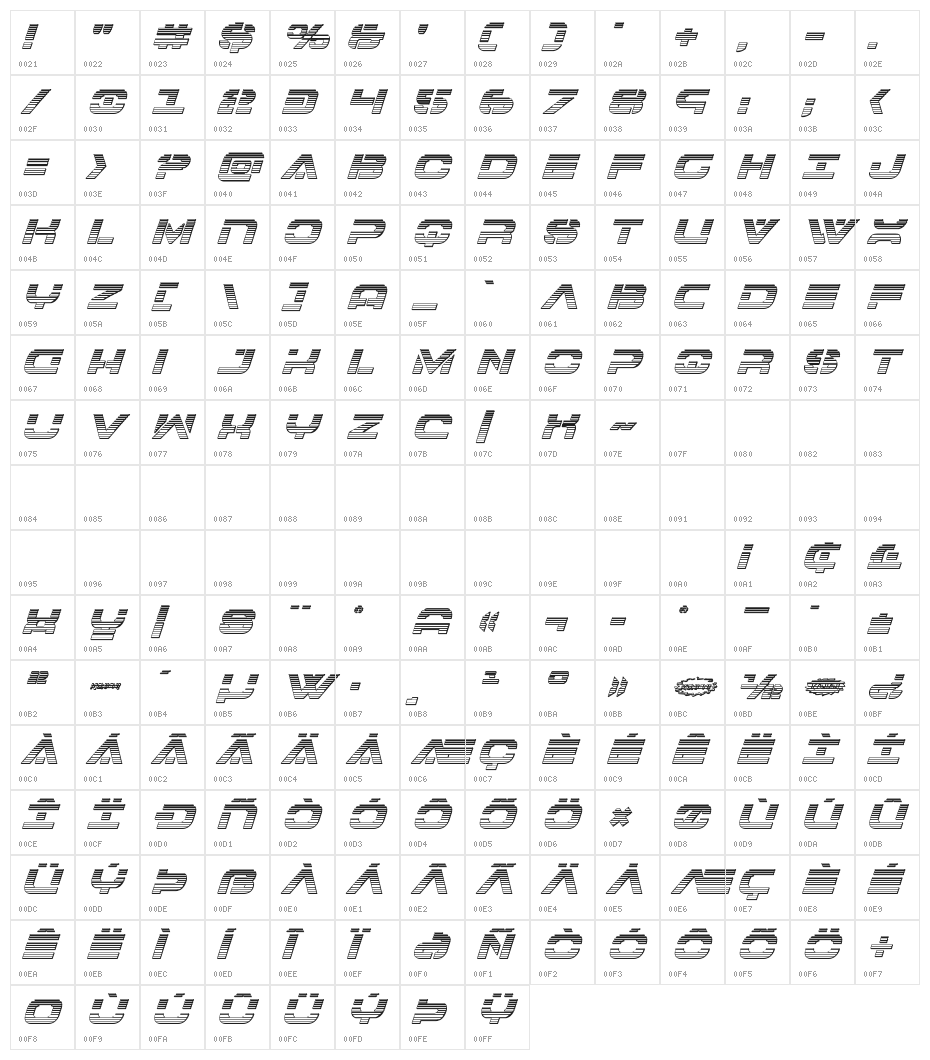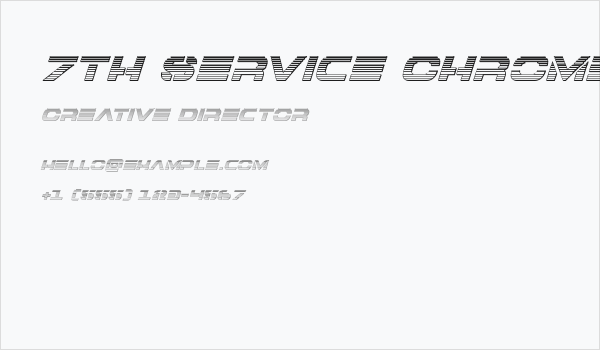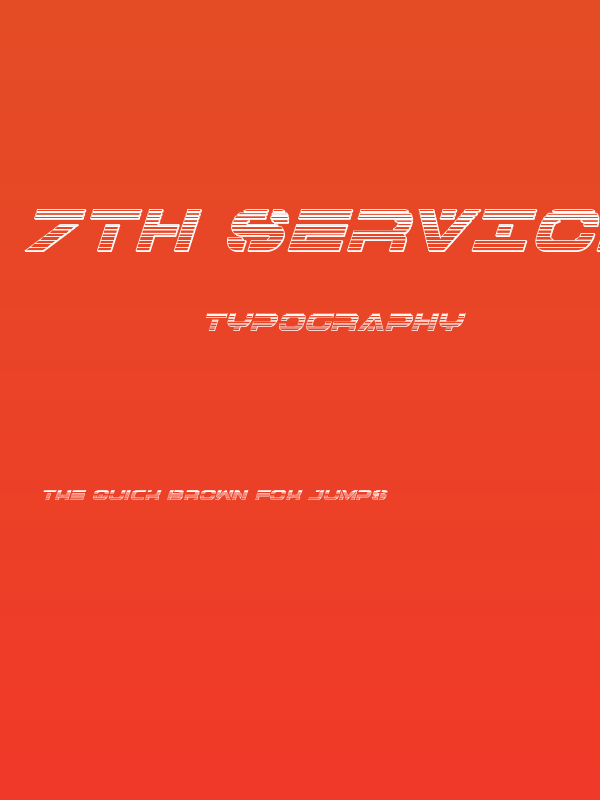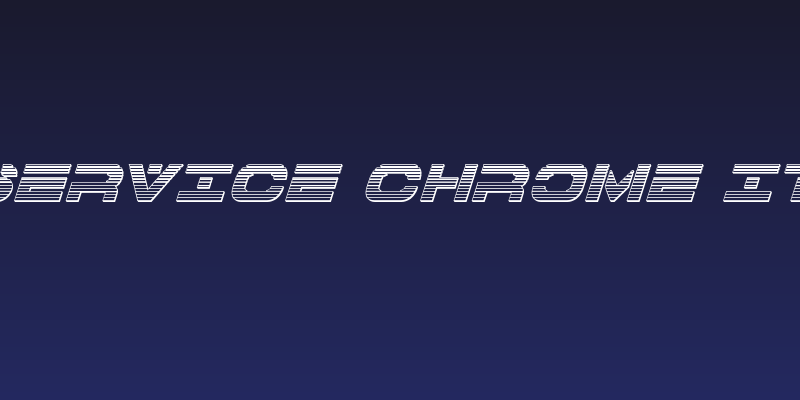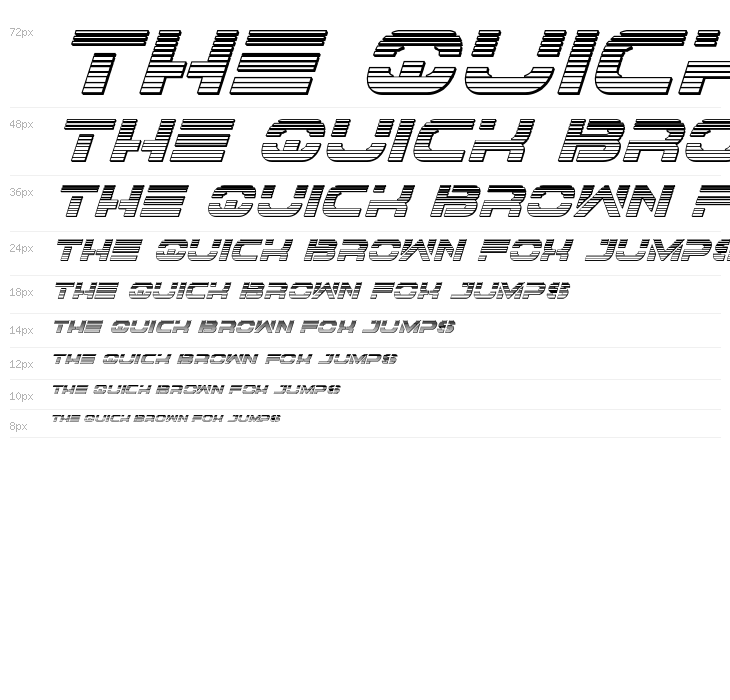
7th Service Chrome Italic Font
| Рекомендуемые проекты | Ideal for technology branding, automotive advertisements, sports team logos, and futuristic-themed posters. |